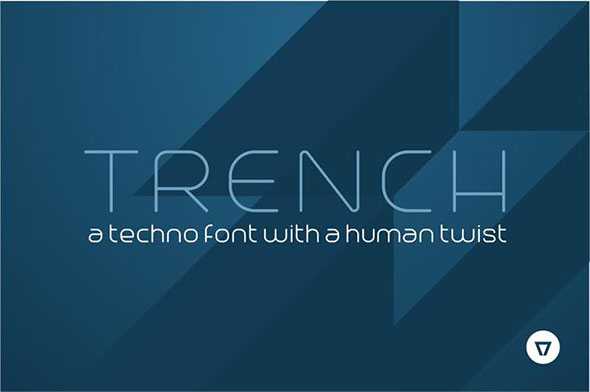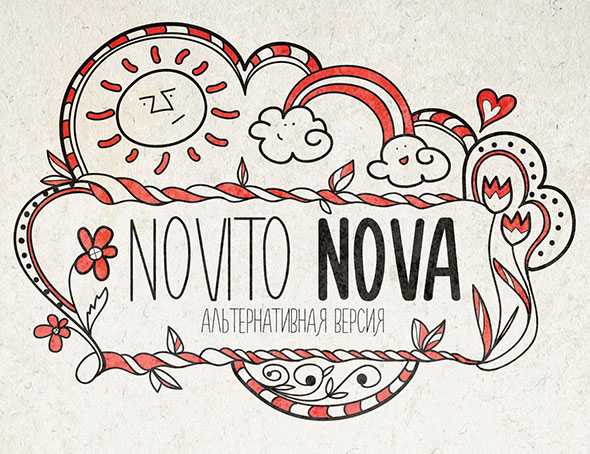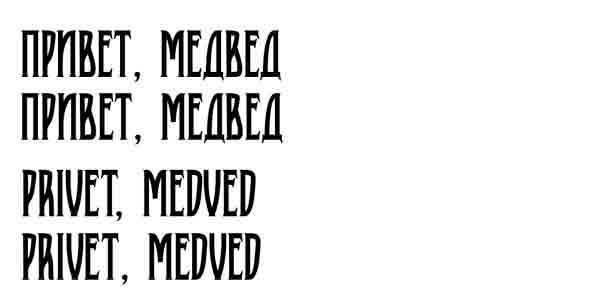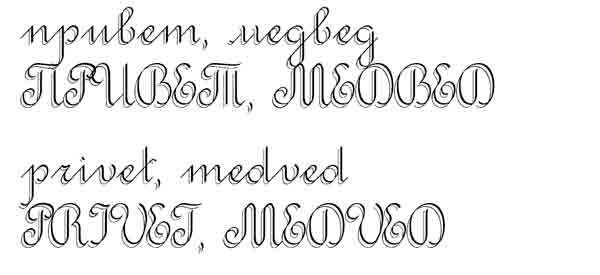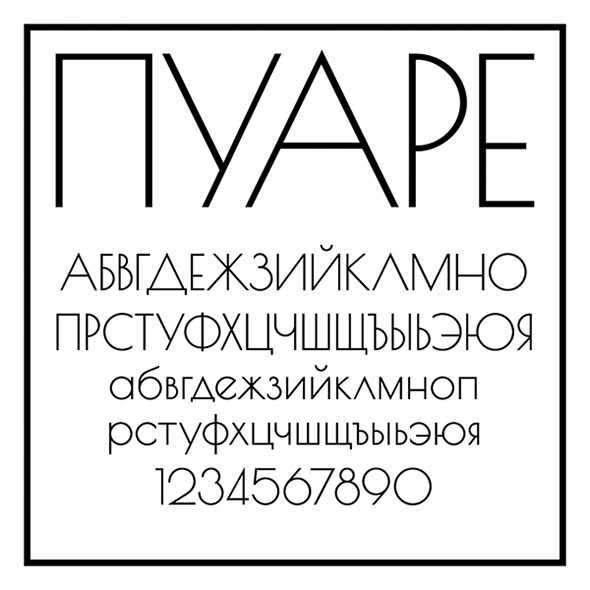
Шрифт для фотошопа тонкий русский – Скачать бесплатно 20 тонких шрифтов для вашего дизайна | DesigNonstop
Бесплатные тонкие шрифты для элегантного дизайна
Ничто не подчеркивает элегантность дизайна как красивый, утонченный шрифт. Типографика оказывает сильнейшее влияние на настроение и стиль всей композиции. Сегодня мы собрали бесплатные тонкие шрифты, которые помогут вам в работе. Первая часть подборки состоит из начертаний, в которых присутствует и кириллическая версия. Пожалуйста будьте внимательны к условиям использования! Некоторые шрифты бесплатны только для личного пользования.
Кириллица
MADE LIKES
Celestina
Novito NOVA
POIRET
Lemon Tuesday
AC Line
Karmina
Arcadia
Латиница
Riverside Avenue
Respective
Trench
Before the Rain
Honeymoon
Canela Bark
Monument_Valley_1.2
35+ русских толстых и жирных шрифтов, обзор сервиса rus-shrift.ru
v_Holy Mackerel!
WiGuru 2
American Captain Cyrillic
Banana Brick
AA BebasNeue
Equestria Cyrillic
Red October Fat
Sprite Graffiti Shadow
Этот жирных шрифт, конечно, больше похож на граффити однако его все равно можно использовать для броских заголовков.
Fantazyor
High Sans Serif 7
Cathodelic Cyr
RUSXXII Dont Mess With Vikings
Deftone
BeeskneesC
Шрифты для Фотошопа русские
Русский шрифт Parnas Deco
Красивый русский шрифт для Фотошопа, который подойдёт для создания большинства печатных изданий и иллюстраций.
Русский шрифт Pasadena Deco
Данный русский шрифт для Adobe Photoshop отличается начертанием и тем, что и прописные и заглавные буквы в шрифте преобразуются в один стиль с заглавными буквами.
Русский шрифт PosteRetro
Заглавные буквы в этом шрифте отличаются от прописных лишь добавлением теней. Размеры прописных и заглавных букв практически одинаковые.Скачать бесплатно русский шрифт для Фотошопа PosteRetro: СКАЧАТЬ ШРИФТ (с ЯндексДиска)
Русский шрифт Proletariat
В этом шрифте и прописные и заглавные буквы одинаковые.
Русский шрифт Severina
Простой русский шрифт для Photoshop с одинаковым начертанием заглавных и прописных букв.
Русский шрифт Stradivari script
Не шрифт, а музыка! Красивые буквы, особенно строчные.